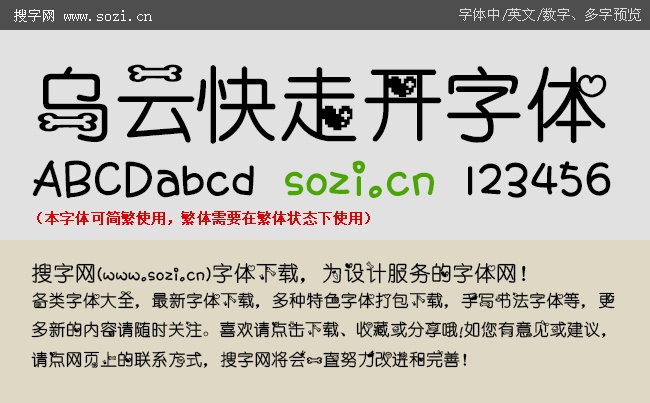
烏云快走開字體
搜字網(wǎng)給大家提供一款烏云快走開字體手機(jī)中文字體下載。這款手機(jī)字體是將圓體字體的個(gè)別筆畫替換成了可愛的卡通圖案。在具備圓字體清晰端正的風(fēng)格同時(shí),卡通味也特別濃,是一款非常可愛的卡通字體,特別適合喜歡手機(jī)字體個(gè)性一些的朋友在手機(jī)上安裝使用。